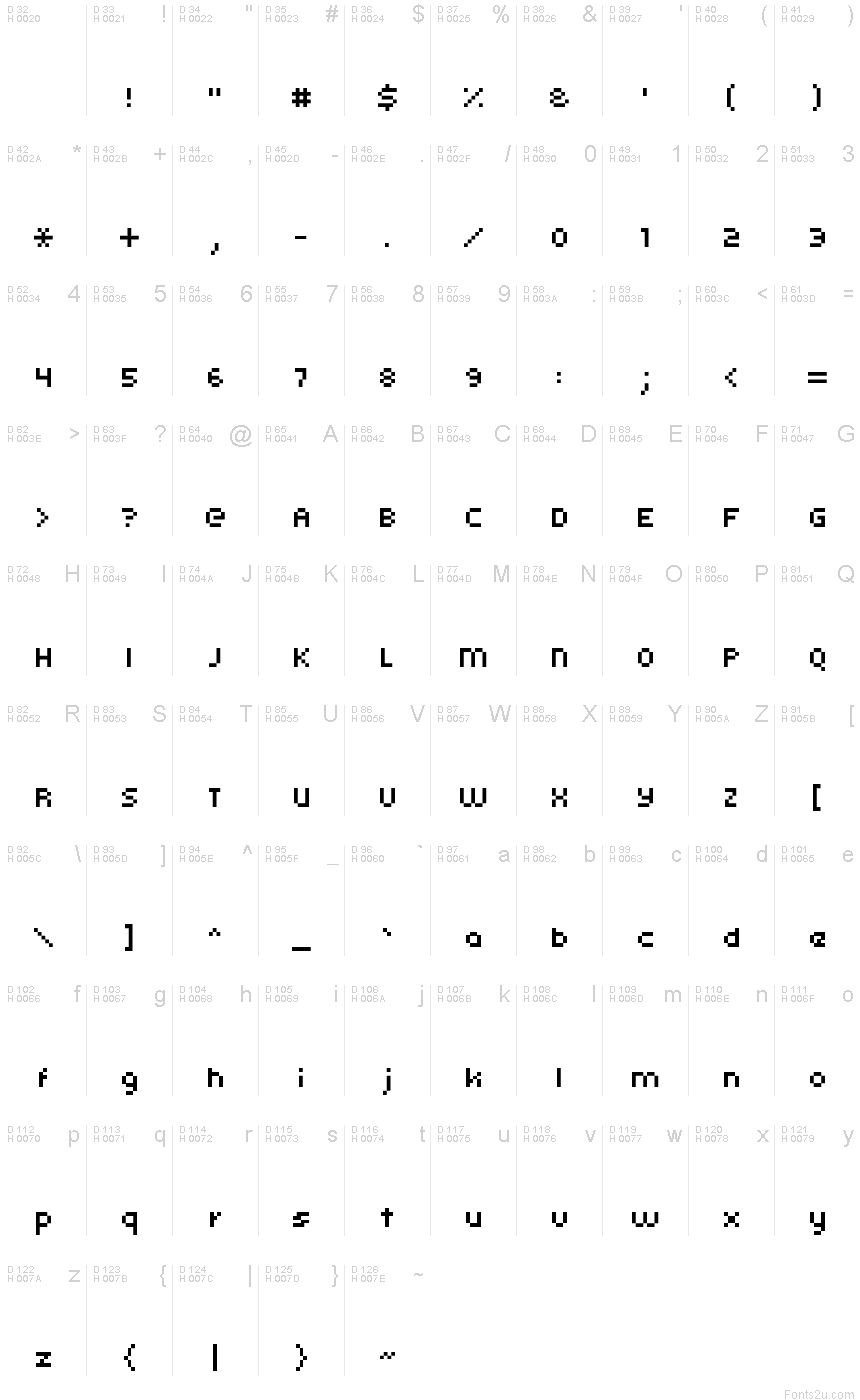
Podgląd czcionki kroeger 05_56
Kroeger 05_56 autorstwa Craiga Kroegera to darmowy, rastrowy font typu bitmap. Charakteryzuje się klockowatymi, kwadratowymi formami i celowo postrzępionymi krawędziami, które nadają każdemu znakowi twardy, surowy rytm niskiej rozdzielczości. Powtarzalne, modularne kształty i otwarte przestrzenie sprawiają, że projekt wydaje się bardziej konstrukcyjny niż wygładzony – niektóre litery bardziej przypominają przycięte geometryczne bloki niż zaokrąglone znaki.
Kroeger 05_56 świetnie sprawdza się w tytułach na plakatach, menu gier, tekstach interfejsów w stylu retro, etykietach technicznych czy krótkich nagłówkach, gdzie pikselowa siatka stanowi główny element wizualny. Ten darmowy font przyda się również do projektowania okładek albumów, zinów i grafik internetowych, które potrzebują surowej, cyfrowej tekstury bez zbędnych ozdobników.